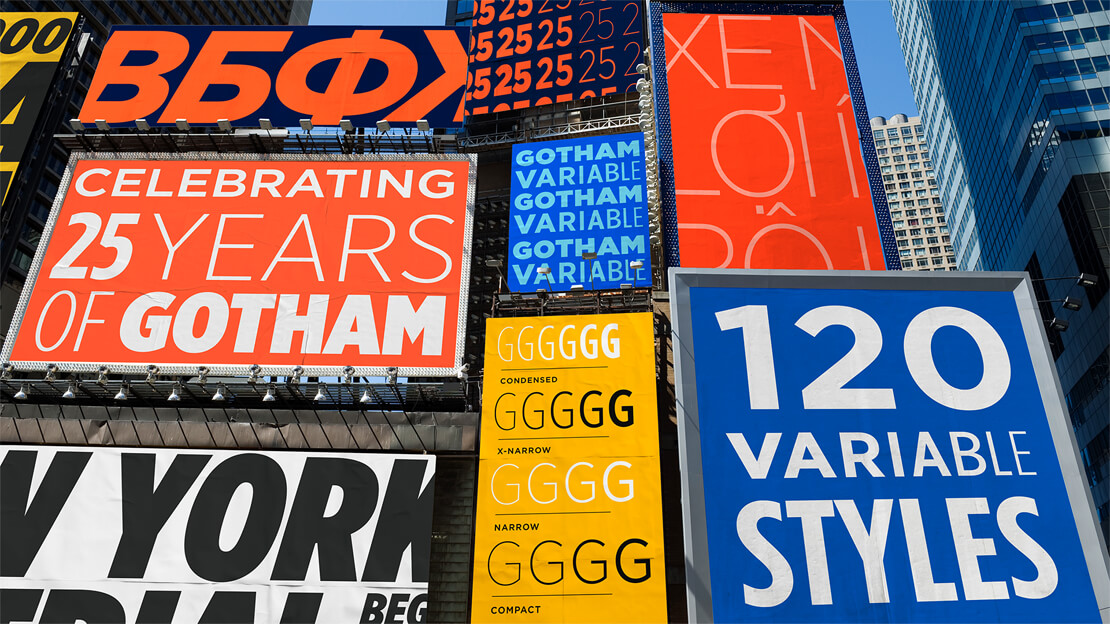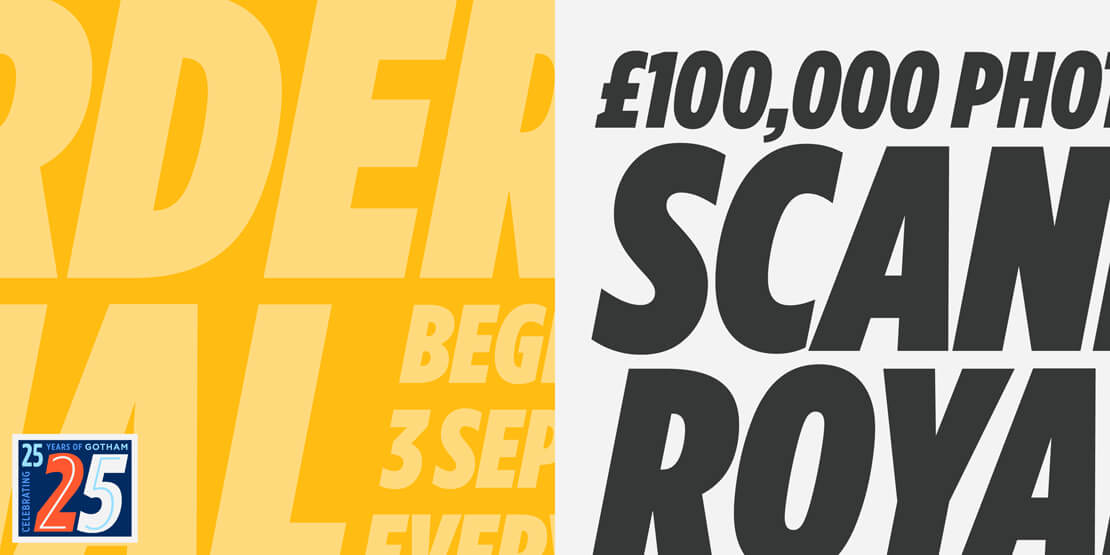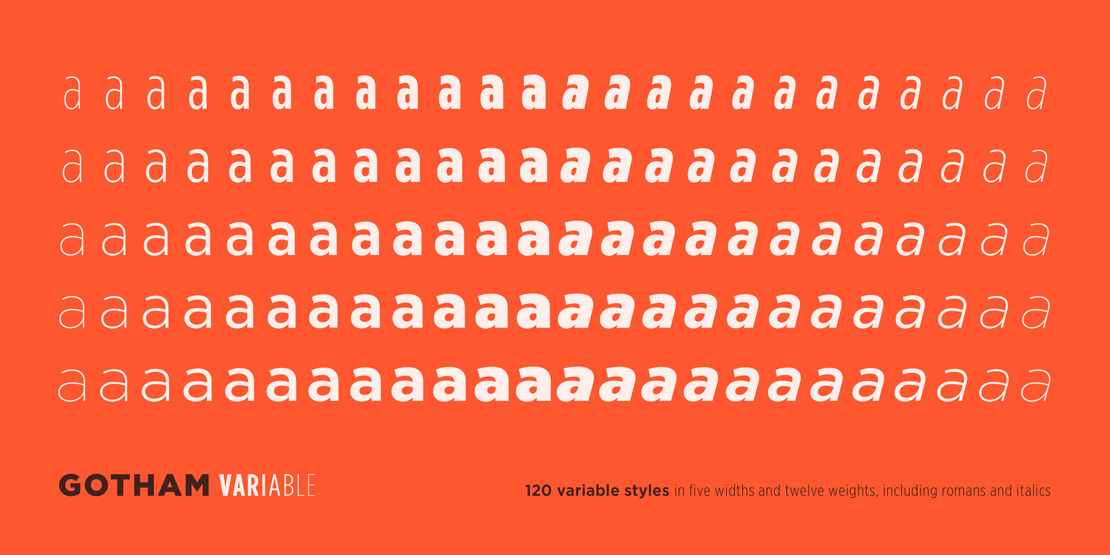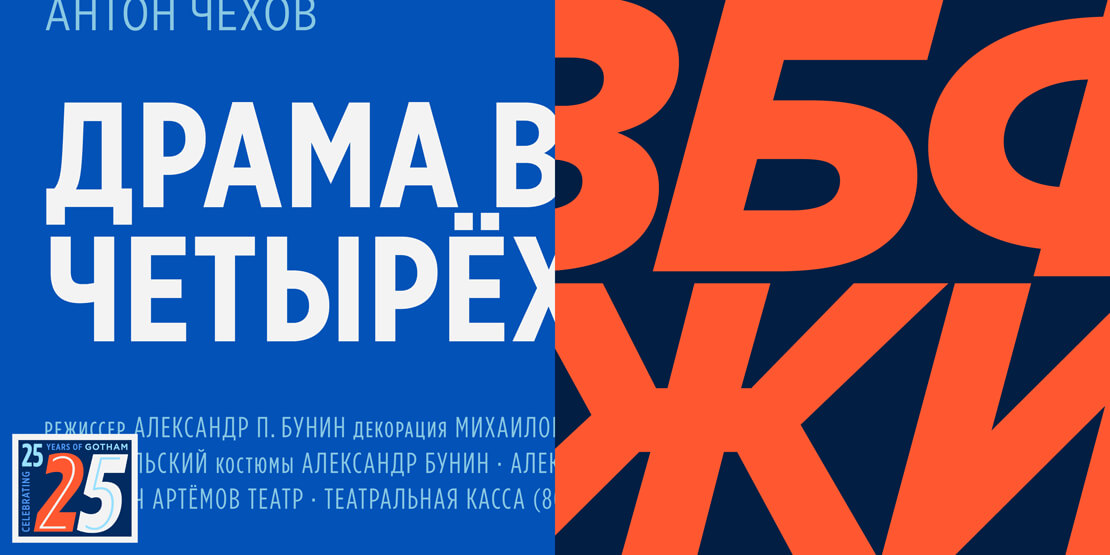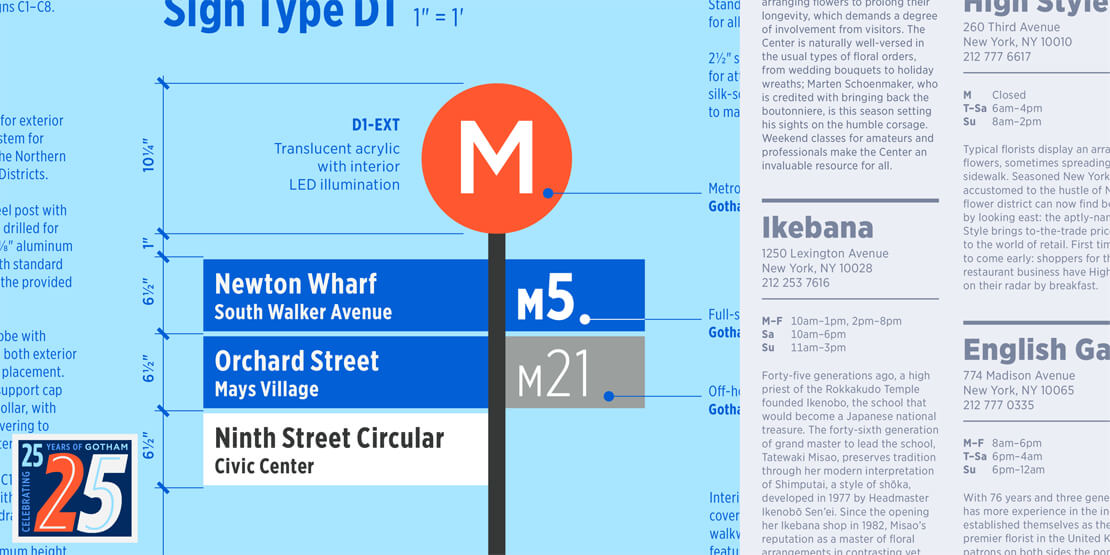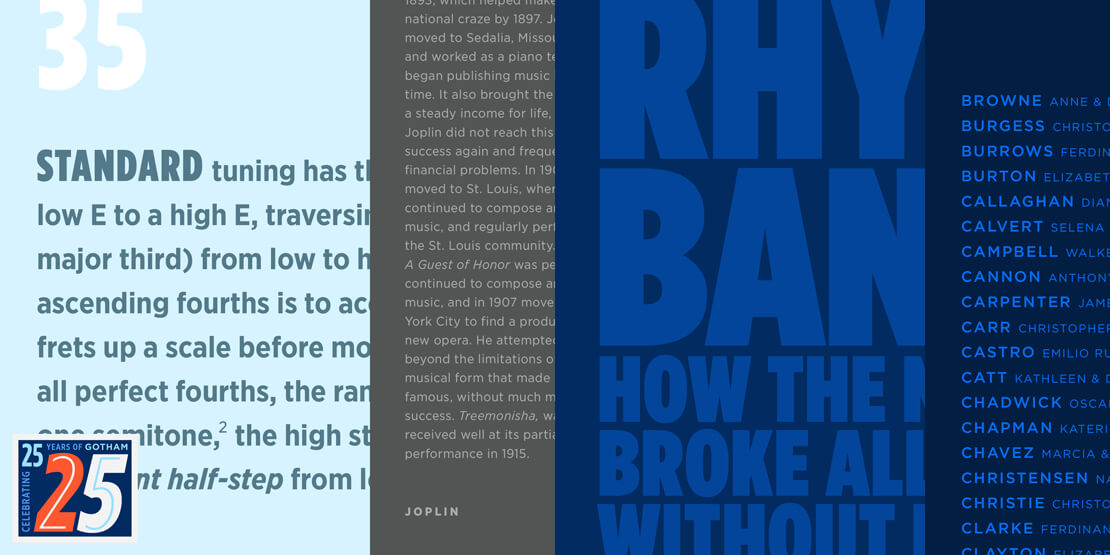
Gotham Variable: Monotype veröffentlicht den Schriftklassiker als Variable Font
Zum 25-jährigen Jubiläum der Schriftart »Gotham« bringt Monotype nun die »Gotham Variable« heraus. Der Variable Font bietet stufenlose Achsen für Gewicht und Breite sowie Unterstützung von weiteren Sprachen.
Seit ihrem ersten Erscheinen auf dem Cover des GQ-Magazins vor 25 Jahren hat sich die ursprünglich von Jonathan Hoefler und Tobias Frere-Jones entworfene Gotham zu einer der weltweit meistgenutzten Schriften entwickelt. Sie prägte das Erscheinungsbild von Marken wie Netflix oder Coca-Cola und erlangte nicht zuletzt durch ihren Einsatz im US-Präsidentschaftswahlkampf von Barack Obama enorme Bekanntheit. Nun stellt Monotype mit der »Gotham Variable« die technische und gestalterische Weiterentwicklung der Schriftfamilie vor.
Stufenlose Anpassung in einer Datei
Durch den Umstieg auf das Variable-Font-Format lassen sich Gewicht und Breite der Schrift nun stufenlos anpassen. Anstatt für jede Ausprägung eine separate statische Datei laden zu müssen, ist das gesamte System in einer einzigen, schlanken Font-Datei gebündelt. Außerdem wird durch die variable Font-Technologie der bisherige Designraum geschlossen: 54 neue Zwischenschnitte sowie eine zusätzliche »Compact«-Breite ergänzen die Familie und sollen neue typografische Spielräume schaffen.
Ausbau der Sprachunterstützung
Die gestalterische Leitung des Projekts lag bei Sara Soskolne (Executive Creative Director bei Monotype), die bereits früher bei Hoefler & Co. an der Schrift mitwirkte. Eine zentrale Vorgabe bei der Erweiterung war es, das vertraute und klare Schriftbild der Gotham exakt zu bewahren.
Neben den technischen Anpassungen wurde auch der Zeichenumfang vergrößert. Die Gotham Variable unterstützt nun Vietnamesisch, wofür komplexe diakritische Zeichen und Tonmarkierungen neu gezeichnet wurden. Darüber hinaus hat das Type-Design-Team die kyrillischen und bulgarischen Zeichensätze überarbeitet und optimiert.